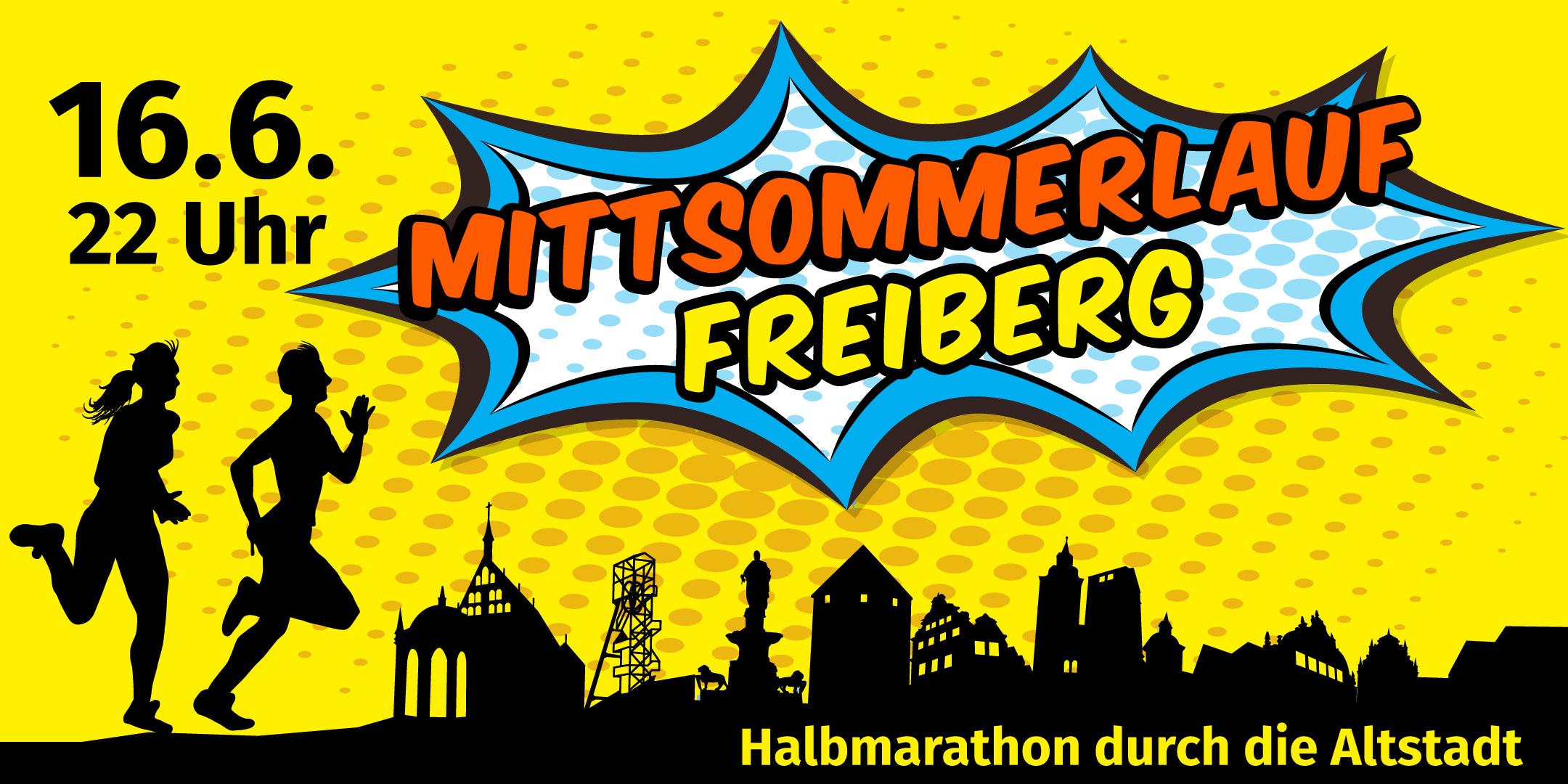
Schrift Midsummer Half
… und nur weil Du den Ring nochmal frei gegeben hast noch ein Gedanke:
Irgendwie stören mich ähnlich wie @StefanV die unterschiedlich schrägen Textwinkel. Außerdem würde ich den Titel noch deutlicher vom Rest der Informationen abheben. Jetzt konkurrieren die Elemente meiner Meinung nach immer noch zu sehr miteinander.
Wie wäre es denn, wenn Du dazu für das Datum und die Zeile unten mal eine aufrechte und schlichtere Serifenlose (vielleicht sogar wieder die Montserrat als Konstante?) probierst?
Gute Idee! Der Aufwand ist auch o.k. Inzwischen ist klar, dass die Sache so auch auf das Plakat kommt :-)
Könnte man die Schriftart eventuell noch in die Montserrat ändern? Die Montserrat sieht ein bisschen "schicker" aus :-).
Mein Fehler – dachte erst die Fira war auf dem letzten Banner, und hatte sie zunächst empfohlen bevor ich nochmal nachgesehen habe.
Die ist wirklich bemerkenswert.
Mmm... Für mich sieht die Eins irgendwie so aus, als würde sie nicht dazugehören. (Die Veranstaltung findet am 6.6. statt und davor steht noch ein halbes T.) Vielleicht hilft es, wenn der Abstand zwischen l und 6 verringert wird...
Ich finde, dass die Vorversion etwas besser ist. Wenn du aber bei der Montserrat bleiben willst: Die Abstände zwischen der 1 und der 6 und der 2 und dem u sind zu groß. Die würde ich etwas reduzieren – den zwischen der 1 und der 6 etwas mehr.
Die Zeile unten vielleicht mal in Versalien probieren?! :-?
Was mir jetzt spontan noch auffällt, ist der "schwebende" Läufer
Ich denke das ist so korrekt - beim Laufen ist man (im Gegensatz zu den Gehern) kurz komplett in der Luft.
Mir gefällt es jetzt viel besser als die Version mit der anderen Schrift ...
Der Versalsatz war ne gute Empfehlung, wirkt aber jetzt etwas reingequetscht. Die Zeile würde ich etwas verkleinern.
Genau, und etwas sperren …
Na ja, das tun Läufer ja auch tatsächlich, er hat sich ja gerade mit dem unteren Bein abgestoßen, während das andere Bein nach Vorn schwingt
die gezeigte Pose liegt ja etwa zwischen Position 2 und 3 in der Bildfolge, da kann der Läufer tatsächlich sich in der Schwebephase befinden.
Vermutlich nimmt die Dauer der Flugphase mit der Geschwindigkeit zu. Der abgebildete Läufer scheint ziemlich langsam zu laufen.